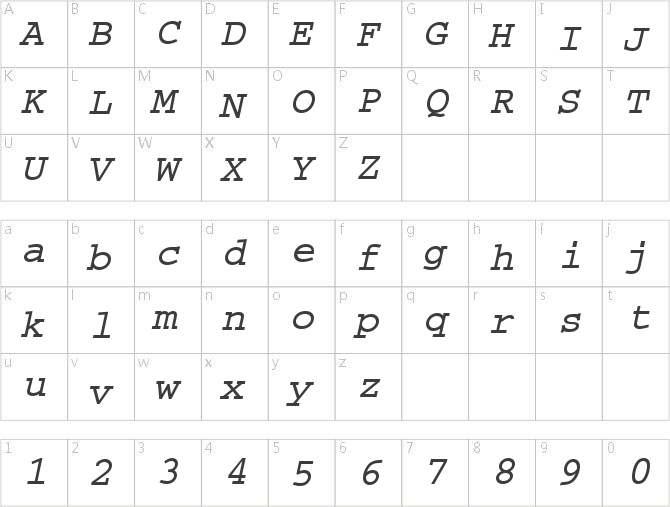
CourierMCY-Bold-Oblique 詳情頁(yè)
CourierMCY-Bold-Oblique字體字庫(kù)是一款讓人賞心悅目、百看不厭的英文字體,適合各類廣告和產(chǎn)品包裝設(shè)計(jì)應(yīng)用,字體大小0.05MB,格式為ttf字體,上傳用戶是凡塵之間,作者/版權(quán)方為未知